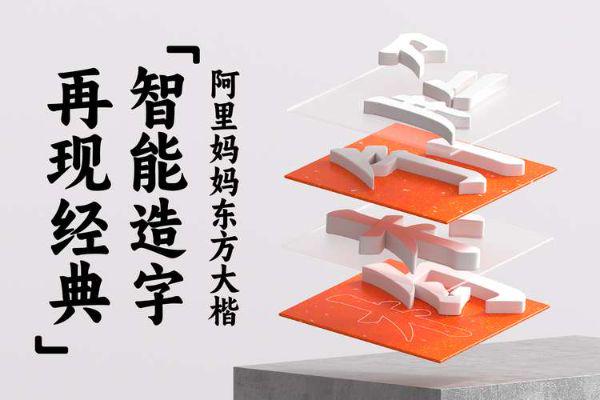
适合制作招牌的字体推荐!7款更适合的字体素材
在店铺装修、品牌视觉设计和商业宣传中,招牌字体往往承担着传递品牌形象的重要作用。一款合适的招牌字体设计不仅需要具备良好的识别度,还需要与店铺定位、经营品类以及整体设计风格相匹配。而你面对众多的字体选择,是不是感觉无从下手?不用担心,下面本文结合不同招牌设计场景,为你精选出7款适合制作招牌的字体,涵盖简约、文艺、传统、商业等多种风格,方便你根据品牌需求进行选择。
1、字由文艺黑
字由文艺黑的整体风格偏向简洁与现代,同时保留了一定的手写感和设计特色。在实际使用过程中,这类字体比较适合咖啡店、书店、生活方式品牌以及创意工作室等场景。
招牌设计通常需要在有限空间内快速传递信息,因此字体的结构清晰度非常重要。字由文艺黑的字形比较规整,笔画之间保持较好的平衡,在远距离观看时依然具有较好的辨识效果。同时,它相比传统黑体更具视觉温度,可以减少商业招牌过于严肃的感觉。
下载招牌字体2、优设好身体
优设好身体是一款在设计领域应用较多的字体,整体风格年轻、清爽,具有较强的视觉表现力。它的字体结构简洁,线条较为流畅,适合用于潮流店铺、餐饮品牌、活动招牌以及年轻化商业空间设计。
在实际设计招牌时,字体不仅需要清楚表达文字内容,还需要体现品牌气质。优设好身体的特点在于字形具有一定亲和感,不会给人距离感,同时又具备现代设计风格。例如奶茶店、服装店、潮玩品牌等场景,都可以通过这类字体增强整体视觉统一性。
3、阿里妈妈东方大楷
阿里妈妈东方大楷是一款具有传统书写风格的字体,适合需要体现文化感和东方特色的招牌设计。它融合了毛笔书写的特点,字体线条具有自然变化,可以为品牌带来更加具有传统气息的视觉效果。
这款字体比较适合茶馆、中式餐饮、文化空间、手工品牌等场景。在设计招牌时,如果品牌希望突出传统文化、手作理念或者东方美学,可以考虑使用类似风格的字体。但书法类字体通常具有较强的风格特点,在使用时建议搭配简洁的版式设计,避免文字信息过多影响招牌实际的功能作用。
4、阿里巴巴普惠体
阿里巴巴普惠体是一款偏现代风格的字体,特点是结构清晰、阅读舒适,适合用于商业招牌和品牌宣传场景。相比一些装饰性较强的字体,它更加注重信息传递效果。
在实际应用中,这类字体适合便利店、科技品牌、服务类门店以及办公空间招牌。由于字体视觉表现较为稳定,即使应用在较大的门头区域,也能够保持较好的阅读体验。对于需要长期使用的品牌招牌来说,简洁耐看的字体通常更容易适应不同阶段的品牌发展。
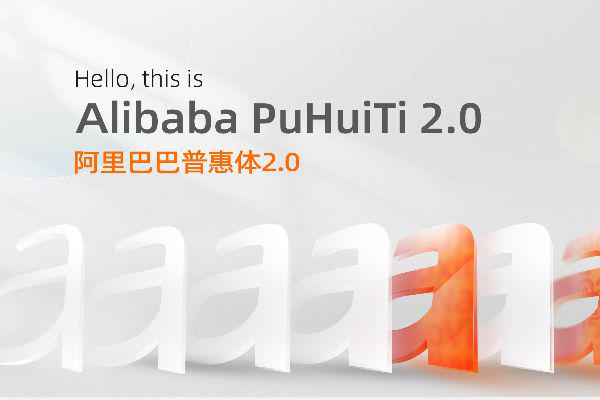
5、抖音美好体
抖音美好体是一款具有轻松、年轻视觉特点的字体,适合用于社交属性较强的商业场景。它的设计风格更加活泼,可以帮助招牌呈现更亲近的品牌氛围。
这类字体适合甜品店、饮品店、儿童品牌、活动空间等年轻化场景。在实际设计中,可以搭配明亮的色彩或者简约图形元素,让整体招牌更加符合年轻消费者的视觉习惯。不过,由于它本身风格较明显,如果应用在强调专业感或高端感的行业中,需要结合品牌定位谨慎选择。
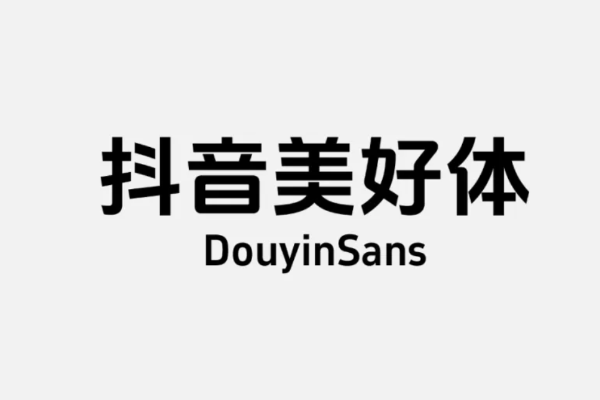
6、思源黑体
思源黑体是一款应用范围较广的现代字体,具有较强的通用性。它的优势在于字形规范、阅读清晰,适合各种商业设计场景。
在制作招牌时,很多品牌需要兼顾美观和实用性,尤其是需要展示较多文字信息的门店。思源黑体能够满足基础的信息展示需求,同时方便与图片、图标以及其他设计元素进行搭配。对于刚开始进行品牌设计的商家来说,这类简洁字体也是比较容易上手的选择。
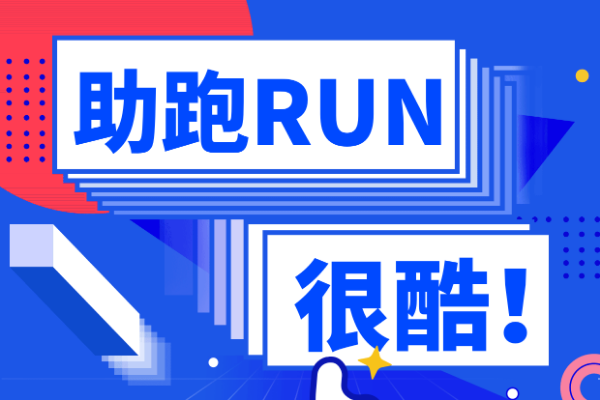
7、汉仪旗黑
汉仪旗黑是一款具有现代商业气质的字体,整体视觉效果简洁大方,适合用于品牌门头、企业标识以及商业空间设计。
它的字体比例协调,笔画设计具有一定力量感,可以帮助招牌呈现更加稳定的视觉效果。对于餐饮连锁、零售品牌以及服务行业来说,这类字体能够在保持专业感的同时,提高品牌识别度。
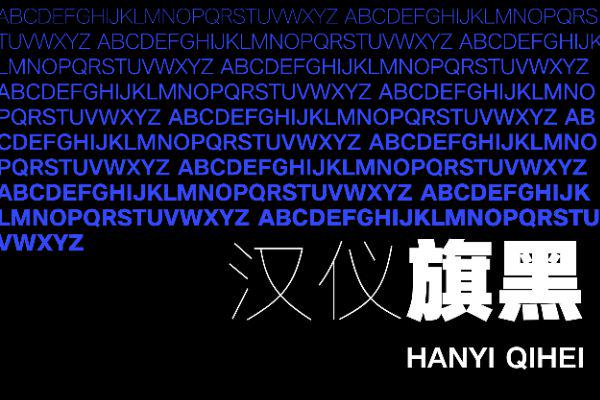
选择适合制作招牌的字体,需要结合品牌定位、使用环境以及字体授权情况综合考虑。不同类型的字体能够传递不同的视觉感受,简洁字体强调清晰和专业,设计字体突出个性和特色,而传统字体则更适合表达文化属性。对于设计师和商家来说,为了更突出招牌设计的表现力,我们可以提前了解选定字体的字体特点,让最终的招牌设计与品牌理念相得益彰。